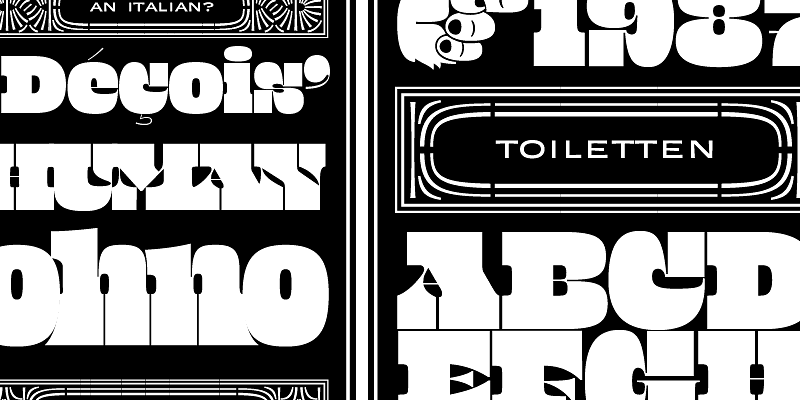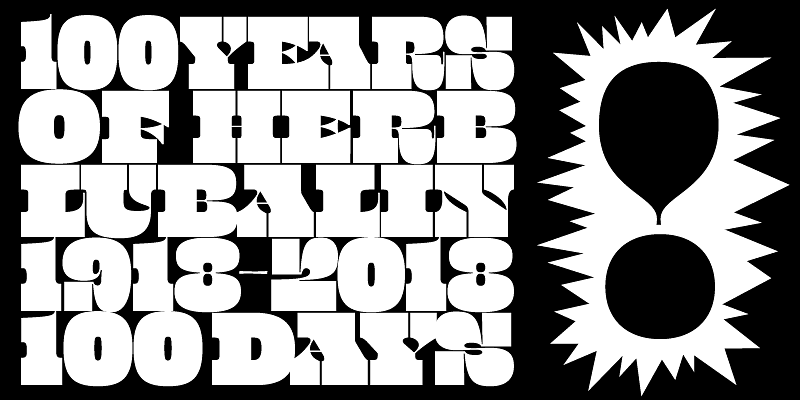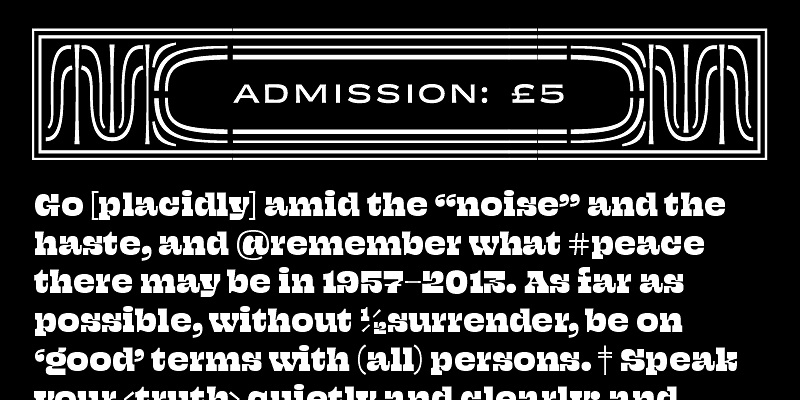
Beastly ist die Sonderschrift, die für das Projekt Lubalin 100 entworfen wurde. Obwohl sie viele der Qualitäten von Lubalins Team von Schriftkünstlern in sich trägt, handelt es sich um ein völlig neues Design. Beastly gibt es in neun optischen Größen, sodass Sie sie in vielen verschiedenen Maßstäben verwenden können.